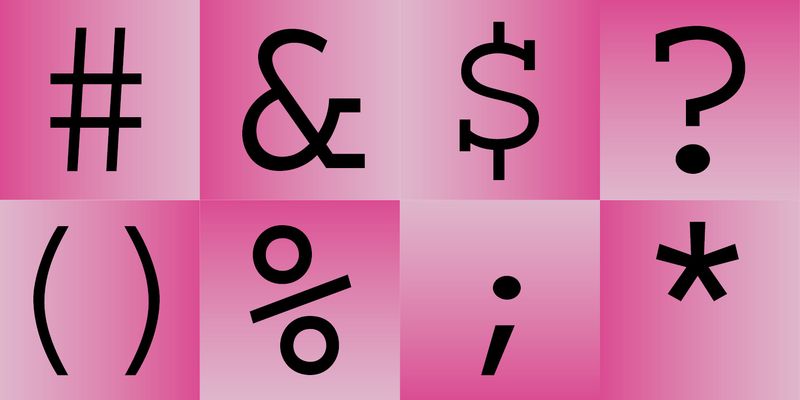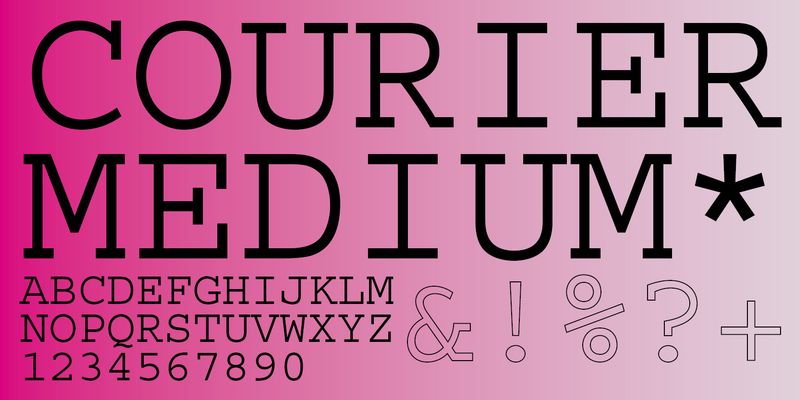
Courier ist eine dicktengleiche Schriftart für die Verwendung in Tabellen, technischer Dokumentation und bei der Textverarbeitung. Die Schrift wurde Mitte der 1900er-Jahre vom IBM-Mitarbeiter Howard Kettler für Schreibmaschinen entwickelt und später von Adrian Frutiger für die IBM Selectric-Serie überarbeitet.